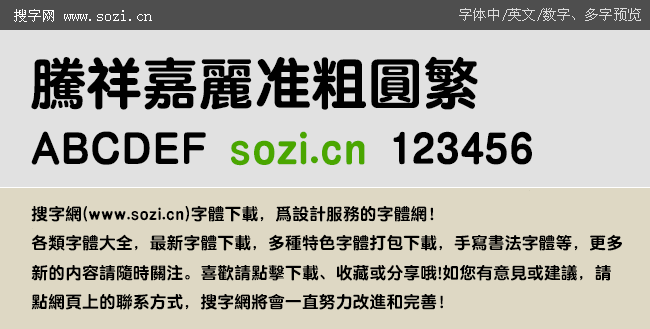
騰祥嘉麗準(zhǔn)粗圓繁
搜字網(wǎng)提供一款騰祥嘉麗準(zhǔn)粗圓繁中文藝術(shù)字體下載,騰祥嘉麗準(zhǔn)粗圓是一款應(yīng)用于設(shè)計(jì)方面的簡(jiǎn)體中文漢字,該字體線條簡(jiǎn)潔圓潤(rùn),字形大方得體,整體效果出眾,并且字庫(kù)完整,可用于藝術(shù)設(shè)計(jì)、包裝印刷、簽名設(shè)計(jì)、圖形設(shè)計(jì)等領(lǐng)域。